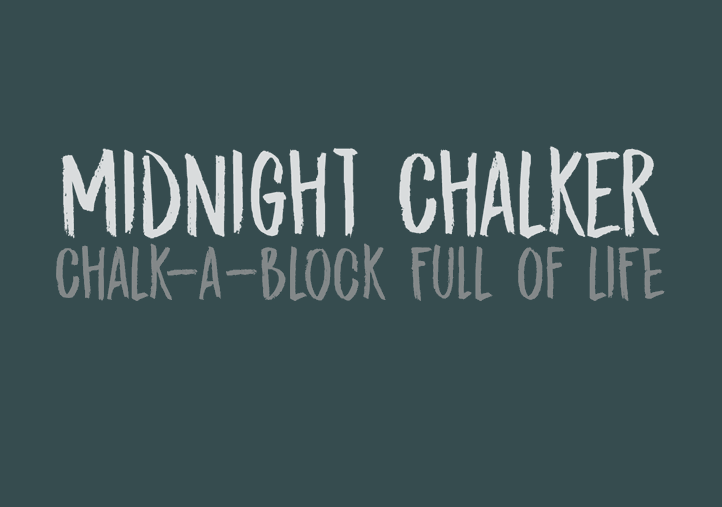
DK Midnight Chalker Font – Fonte Grátis
DK Midnight Chalker Font
A fonte ‘DK Midnight Chalker Font’ é uma delícia para os olhos, ideal para quem deseja adicionar um toque de sofisticação a qualquer projeto visual. Com suas linhas elegantes e textura rústica, esta fonte brush é perfeita tanto para trabalhos pessoais quanto para projetos comerciais, desde que você compre a versão completa, que oferece tudo o que precisa para garantir uma experiência de uso sem problemas. Compreendendo as regras da categoria Brush Fonts e criada pelo designer David Kerkhoff, esta fonte é um dos ícones de gráficos digitais que adoraríamos introduzir em nossos projetos. Ela pode ser usada livremente para fins pessoais, mas para aplicações comerciais como aplicativos, jogos ou software, você precisará comprar a versão completa e comprar os direitos de uso que vêm com o pacote. A fonte traz um conjunto completo de caracteres, incluindo todos os símbolos especiais, garantindo que seu design final será impecável. Eles foram cuidadosamente projetados para garantir uma boa leitura tanto em grandes fontes quanto nas menores, proporcionando um estilo único e profissional a qualquer projeto onde for usada. Se você estiver procurando por mais recursos gráficos ou adorar desfrutar da beleza desta fonte, visite www.hanodedfonts.com para obter mais detalhes sobre como utilizá-la de maneira legal.